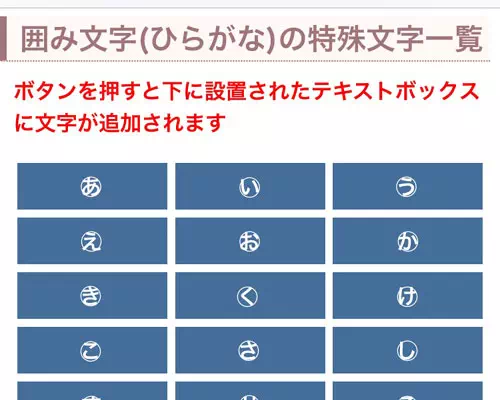
丸囲み文字のひらがなとカタカナ一覧!特殊文字ひらがなをコピペできます
最近のインスタやツイッターでは特殊文字を使って名前やプロフィールを書いてる人が目立ちます。
英語やアルファベットなどの特殊文字は色々あって可愛い文字も多いですが、ひらがなやカタカナの特殊文字ってあまり見かけませんよね。
ひらがなやカタカナの特殊文字で言えば一番有名なのが文字を『○』記号で囲った丸囲み文字です。
丸囲み文字を使ってプロフィールを作りたいけど丸囲み文字の変換方法がわからなくて困っているという方もいるのではないでしょうか。
そこでこのページではひらがなとカタカナの特殊文字である『丸囲み文字』を一覧で用意しました。
ひらがなやカタカナの特殊文字を使いたい方はこちらからコピペして自由にお使いください。
丸囲み文字のひらがな一覧(特殊文字)
以下は特殊文字の丸囲み文字ひらがな一覧です。
あ⃝い⃝う⃝え⃝お⃝
か⃝き⃝く⃝け⃝こ⃝
さ⃝し⃝す⃝せ⃝そ⃝
た⃝ち⃝つ⃝て⃝と⃝
な⃝に⃝ぬ⃝ね⃝の⃝
は⃝ひ⃝ふ⃝へ⃝ほ⃝
ま⃝み⃝む⃝め⃝も⃝
や⃝ゆ⃝よ⃝
ら⃝り⃝る⃝れ⃝ろ⃝
わ⃝を⃝ん⃝
丸囲み文字のカタカナ一覧(特殊文字)
以下はカタカナを丸囲みした特殊文字の一覧です。
㋐㋑㋒㋓㋔
㋕㋖㋗㋘㋙
㋚㋛㋜㋝㋞
㋟㋠㋡㋢㋣
㋤㋥㋦㋧㋨
㋩㋪㋫㋬㋭
㋮㋯㋰㋱㋲
㋳㋴㋵
㋶㋷㋸㋹㋺
㋻㋾ン⃝
ひらがなと同様に、カタカナを四角囲みした特殊文字もあります。
丸囲み文字以外のひらがなとカタカナ特殊文字を使いたい時
ひらがなもカタカナも丸囲み文字は意外と多くの方が使っている特殊文字ですが、実は囲み文字以外の特殊文字もあったりします。
例えば、下線やドットは定番として、珍しい星マークやニコちゃんマークのような顔文字付きの特殊文字などもあります。
【星マーク】
あ͙い͙う͙え͙お͙
【顔文字】
ア̤̫イ̤̫ウ̤̫エ̤̫オ̤̫
インスタで丸囲み文字を活用する方法
インスタグラムの投稿やプロフィールに丸囲み文字を使うと個性を際立たせることができます。
特にストーリーズやキャプションで使うと目を引きやすくなりフォロワーの注目を集められるでしょう。
このセクションでは実際にどのように丸囲み文字を活用できるかを解説します。
具体的なシーン別の使用方法や注意点を参考にして自分だけのオリジナルスタイルを作りましょう。
プロフィール・投稿での映える使い方
インスタプロフィールでは名前や説明文に丸囲み文字を加えることで目立たせることができます。
たとえば、「好きなこと【🍓趣味】」など、要点を囲んだり装飾を組み合わせて強調しましょう。
また、投稿のキャプションで特別な言葉を丸囲み文字にすると強調したい情報を目立たせる効果があります。
ハッシュタグや説明文に使用すると視覚的な違いを生むことができますが使いすぎには注意が必要です。
丸囲み文字が表示されない場合の対処法
丸囲み文字は一部の古い端末や特定のフォント環境では正しく表示されないことがあります。
そのため表示されるか不安な場合は事前に複数のデバイスで確認するのがおすすめです。
またWebフォントに依存するサイトやSNSプラットフォームによっても再現性が異なるため汎用性の高い文字を優先的に使うと安心です。
どうしても表示が不安定な場合は代替文字や絵文字を組み合わせるなどの工夫で視認性を補うことができます。
読者の環境を考慮した丁寧な装飾を心がけましょう。
フォントや背景で変わる見え方の違い
丸囲み文字は使用するフォントや背景色によって印象が大きく変わります。
SNSやブログではデフォルトのフォントに合わせて文字が表示されるため環境の違いによって丸の形が微妙に変化することがあります。
また背景色が濃い場合には白抜きの丸囲み文字が見えにくくなることもあります。
視認性を高めたいときは背景とのコントラストを意識し丸囲み文字が埋もれないよう調整してください。
ブログではスタイルシート(CSS)で表示フォントが変わることがあるため自分のテーマに合わせて最適な丸囲み文字を選ぶとよいでしょう。
実際に複数のパターンを試して見え方を比較するとより読みやすいデザインを作りやすくなります。
丸囲み文字の最新トレンドとSNSでの効果
最近のSNSではシンプルで見やすいデザインが好まれるため丸囲み文字は「視線誘導」や「カテゴリ分け」に活用されることが多くなっています。
特にインスタグラムではハイライト名やプロフィール項目に丸囲み文字を取り入れることで統一感が出てアカウント全体の印象が整いやすくなります。
またストーリーズに丸囲み数字を入れることで複数スライドの順番を見せやすくなり離脱防止にもつながるでしょう。
ブログでも記事内の流れを整理するために丸囲み文字を使うことで読者の理解が深まりやすくなります。
今後も視覚的にわかりやすい表現が好まれる傾向は続くため丸囲み文字はさまざまなシーンで活用できるでしょう。
インスタやブログで丸囲み文字が表示されない原因と対処法
丸囲み文字はインスタやブログLINEなどさまざまなサービスで利用できますが利用する環境によっては正しく表示されない場合があります。
特に「㋐」のような丸囲みカタカナはUnicodeに対応したフォントで表示されるため古いOSやブラウザでは文字化けしたり「□(豆腐)」と表示されたりすることがあります。
またひらがなの丸囲み文字は正式なUnicode文字ではなく「ひらがな」と「◯」を組み合わせた特殊な表現を使用しているため環境によって見え方が異なる場合があります。
まとめ
ひらがなやカタカナの特殊文字は英語と比べると数も少なくて少し見劣りする部分もありますが、日本人としてはひらがなやカタカナもオシャレに使いたいですよね。